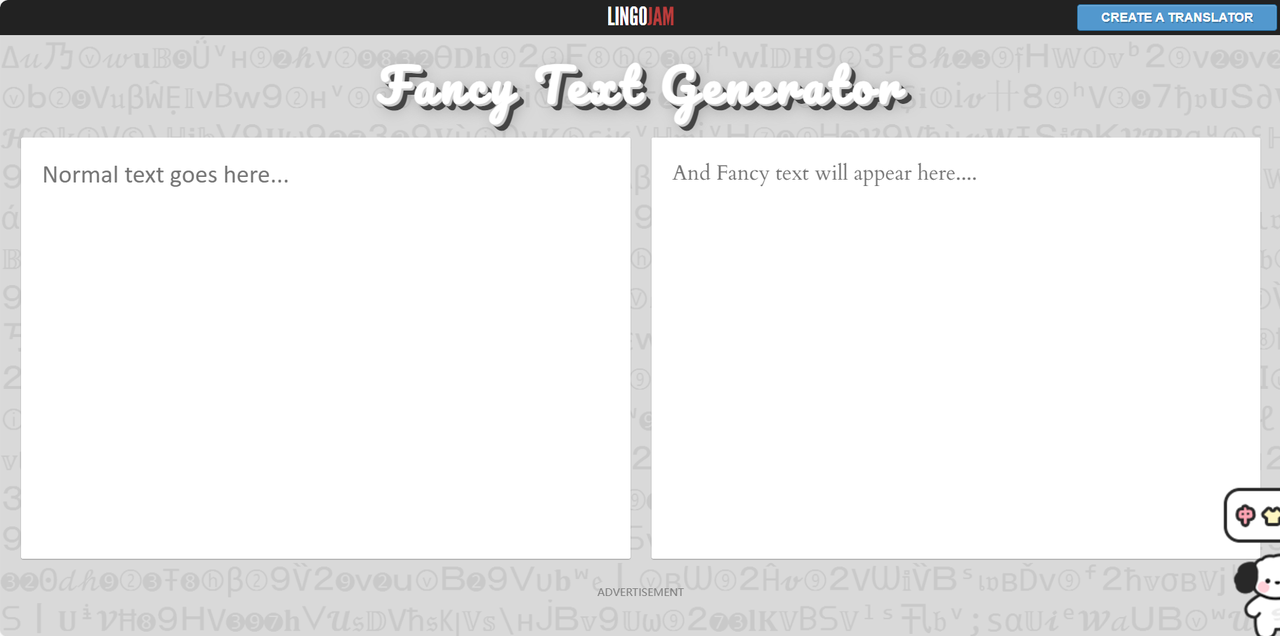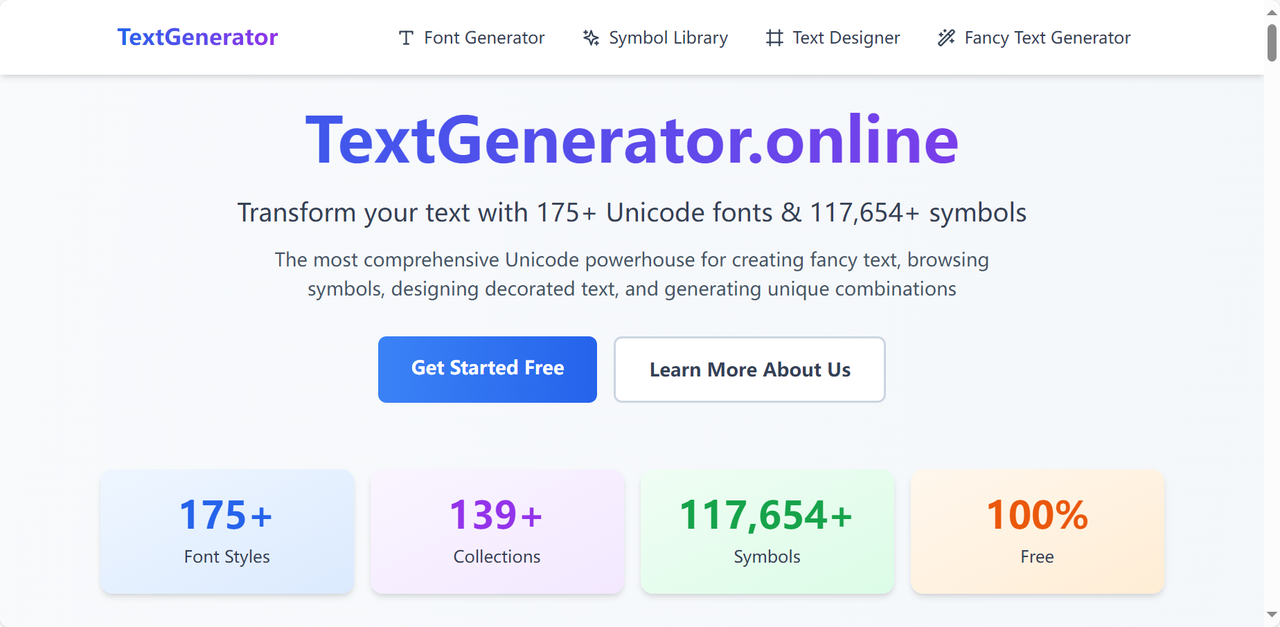
花样字体生成器在线使用,无需下载,炫酷文字一键转换
觉得自己的文字太普通,想让普通文字变成吸睛艺术字?花样字体生成器是从设计小白到创意设计师的必备工具之一,无需下载任何字体资源包,在线就能一键转换花样字体。市面上很多字体生成器要么是操作复杂看不懂,要么可能有侵权的风险。我给大家整理了 6 款合规且好用的在线花样字体生成器,零基础也能几秒制作出酷炫的花样字体,不管是科技风、中国风,还是可爱风、简约风,通通一键搞定!掌握这些花样字体生成器的用法,普通的设计作品也能一秒吸引到别人的视线,为你提升更多的关注度。
一、字由
作为国内领先的字体管理工具,字由凭借其【AI 字体】功能,成为了很多用户生成花样字体的首选。在这里,你可以直接输入自己想要的字体类型,也可以按照语言、场景、风格进行精准筛选。选择你心仪的花样字体,输入文本内容,点击【立即生成】,30s 之内就可以获得对应的花样字体了。无需任何设计技能,也能拥有好看的字体!如果第一次生成的花样字体不满意,还可以让它多次重新生成后,满意的字体可以选择默认背景或透明背景来下载,一般会下载为我们常用的 PNG 格式,便于后续应用到各大设计软件当中。
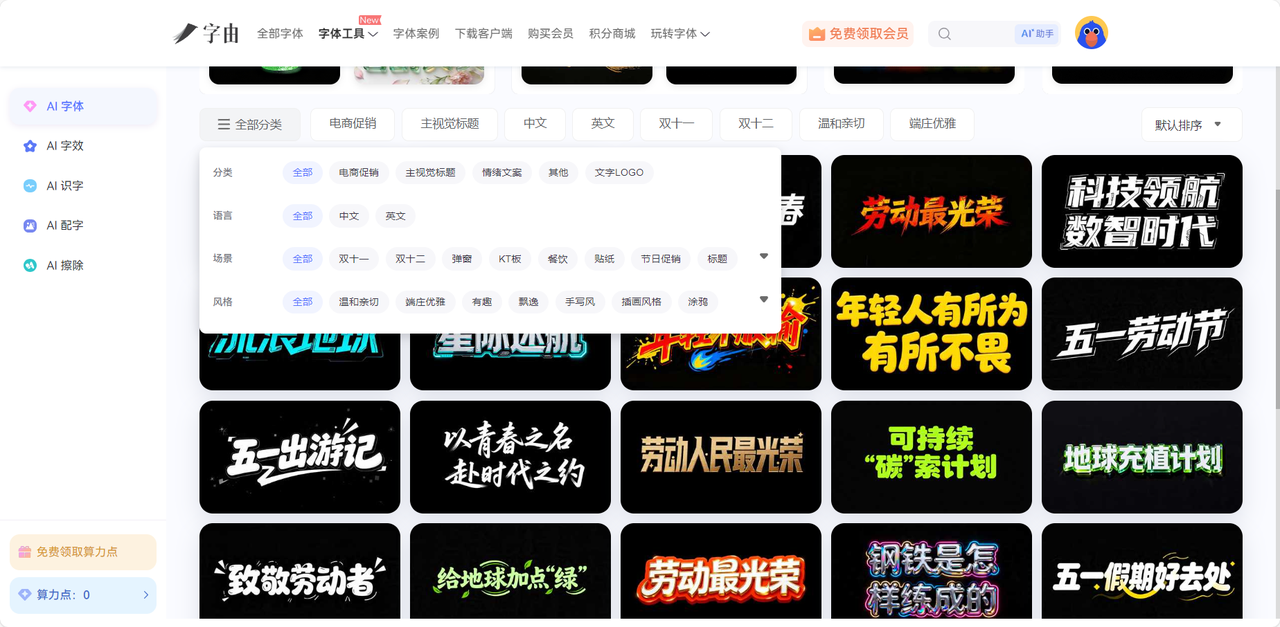
二、LingoJam
LingoJam 是海外最具口碑的字体转换工具,内置150+种主流花样字体,比如花体手写、泡泡体、霓虹线条、镂空方框、科技像素等多种风格,满足大量的花体字设计需求。LingoJam 采用实时渲染技术,只要输入文字就可以快速生成花体字,支持中英文、数字、符号、 emoji 混合转换,字符覆盖率99%,且生成的文本可以直接复制粘贴,适配各类全球主流社交平台,无需安装字体,不受设备限制。同时,它还支持长文本批量转换,自动适配排版,步骤简单,操作便捷,新手用户也可以尝试。
三、TextGenerator.online
TextGenerator.online 是一款全能型的花样字体生成平台,字体数量多,功能丰富,符号库资源齐全,非常适合需要丰富字体效果以及深度定制花体字的用户。它的功能模块包含花样字体生成、文本装饰器、特殊格式转换、多文本排版、符号浏览器、文字加密6 种核心工具,一站式满足用户需求。自带的字体资源及户可以涵盖大部分需求,且每款字体渲染精细,笔画完整。除此之外,TextGenerator.online 最大的特色就是拥有最大的符号装饰库,包含上万种特殊符号、emoji、装饰线条、边框、表情符号、星座符号、游戏图标等,可自由组合插入文本,实现极致个性化的花体字生成。虽然是国外的字体生成器,但是界面采用结构化布局,左侧是功能区,右侧是样式区,中间是预览区,操作直观。
四、StylishText.io
StylishText.io 是一款轻量级的花样字体生成器拥有超高稳定性和极简页面,适合追求简洁高效的用户。想要生成花样字体,只需要输入文字,选择样式,再复制文字就可以了,无需任何技术含量,谁都可以快速获得花样字体。支持无限次转换,无字符数量限制,且每次都是免费的。和其他转换器相比,StylishText.io 自适应所有设备,手机平板电脑均可以流畅使用,每款字体都是经过测试的,确保在不同设备都能呈现出最佳效果,是日常可以快速生成高质量花样字体的最佳选择。它最大的优势就是提供兼容性提示,当你输入文本内容之后,StylishText.io 推荐的每款花样字体都会自动标注在不同平台的显示效果,便于你更快地选出最合适的字体。
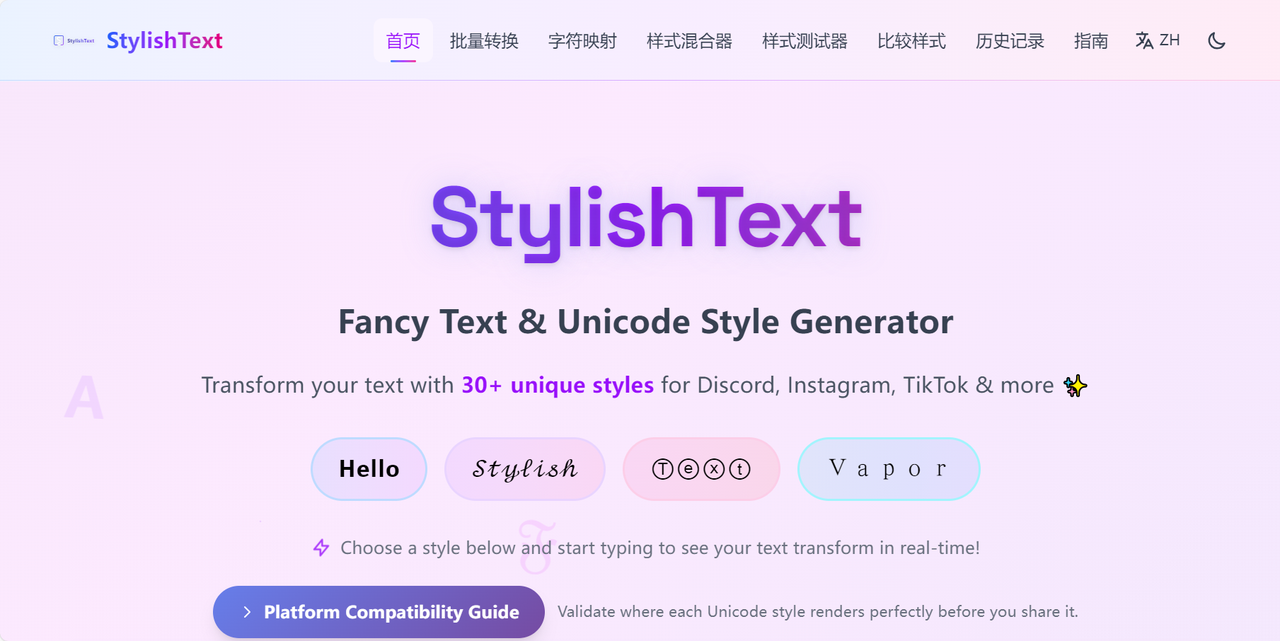
五、Calligraphr
Calligraphr 是一款极具特色的在线花样字体生成器,允许用户将自己的手写字体转换为可在电脑上使用的字体文件。它提供超多可打印的花样字体模板,用户可以根据模板在纸上书写想要的内容,拍照上传,Calligraphr 会自动识别并生成一套完整连贯的个性化手写字体,这是专属你的独一无二的字体。生成的花样字体不仅质量高,支持个性化调整,同时版权归自己所有,商业用途也完全没问题。唯一的缺点是高级功能需要付费解锁,比如添加更多字符、优化细节,一般来讲免费版本也可以完全满足大部分用户的需求了。用过很多字体转换器,我觉得这款工具算是最还原真实手写风格的花样字体的工具了,它是真的模仿了人类书写时的笔触,笔画粗细过渡自然,这种花样字体更带着一种手写质感的温度,对于追求个性化好人手作温度的设计师来讲,选择它就能简单创造花样字体。
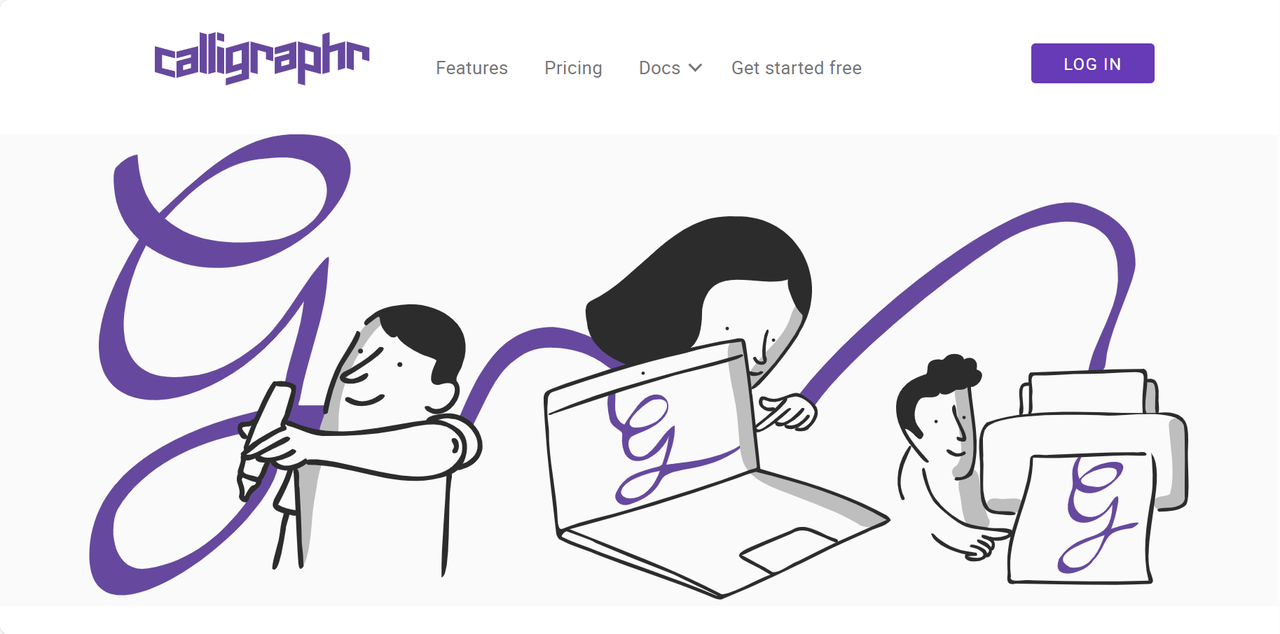
六、Freaky Font Generator
Freaky Font Generator 是美国开发的新锐花样字体工具,主打走在潮流前沿,追求独特个性的视觉体验,这里的花样字体风格更加前卫,更加大胆,更加吸睛,喜欢这类风格的小伙伴可以来免费尝试一下。就我个人的使用体验来讲,Freaky Font Generator 最核心的优势还是独家潮流字体库,除了一些基础款字体,收录了大量海外最新的潮流爆款花体字,比如酸性设计、赛博朋克、哥特纹身、故障艺术、魔法符文等,这些还都是平台原创字体,不会与其他设计撞款。用户选中心仪的字体之后,还可以自主添加阴影、发光、抖动等多种视觉特效,让你的花样字体更加丰富生动,富有层次感。
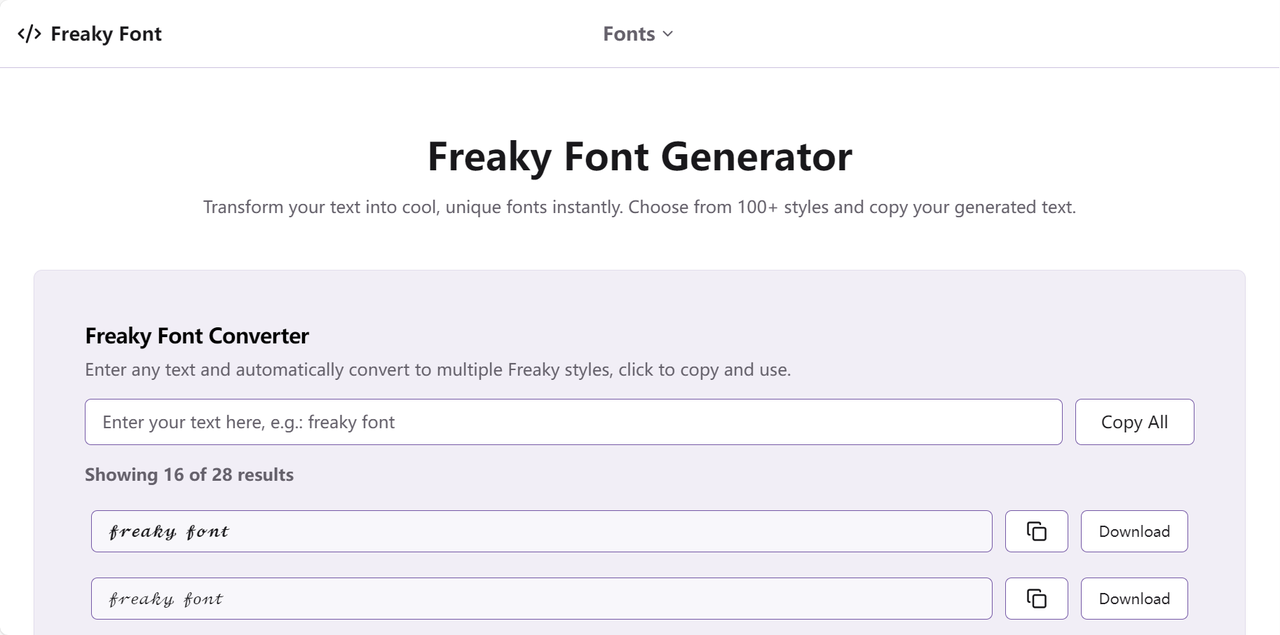
以上 6 款花样字体生成器满足了设计行业的各个场景需求,从特效设计、logo 设计、品牌设计到社交媒体文本以及手写字体的设计,有了这些工具的帮忙,都可以轻松完成!其中,字由的 AI 字体功能是生成中文花样字体的绝佳神器,而其他字体生成器则为我们打开了全球化的字体资源库,大家可以根据自己的需求以及使用场景,自行选择 1-2 个合适的工具配合使用,效果会更好哦。